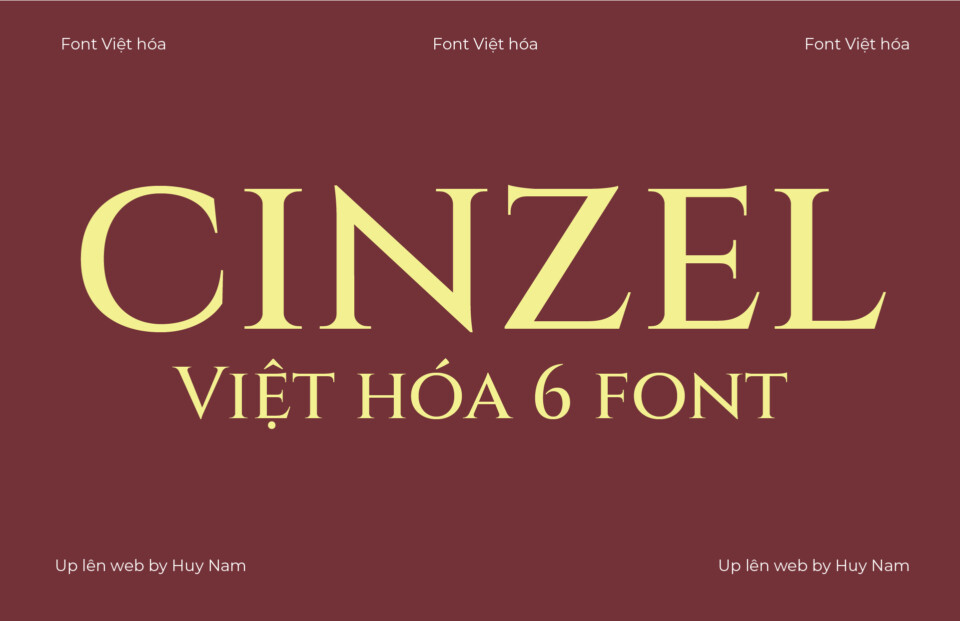
Font Việt hóa Cizel ( 6 font )
Tải Ngay Bộ Font Việt hóa Cizel ( 6 font ) Sang Trọng Cho Thiết Kế Cổ Điển
Trong thế giới đồ họa hiện đại, việc tìm kiếm một bộ Font Miễn Phí chất lượng cao luôn là ưu tiên hàng đầu của các nhà thiết kế. Đặc biệt, đối với những dự án mang phong cách cổ điển, uy nghi và mạnh mẽ, bộ Font Việt hóa Cizel ( 6 font ) chính là sự lựa chọn không thể bỏ qua. Cizel được lấy cảm hứng từ các ký tự khắc trên đá của đế chế La Mã cổ đại, mang đến một vẻ đẹp vượt thời gian nhưng vẫn đảm bảo tính ứng dụng linh hoạt trong các phần mềm thiết kế hiện nay. Với sự tỉ mỉ trong quá trình việt hóa, bộ font này giúp người dùng dễ dàng thể hiện các nội dung tiếng Việt mà không lo lỗi dấu hay khoảng cách chữ không đều, tạo nên sự đồng nhất hoàn hảo cho tác phẩm.
Đặc điểm nổi bật của bộ Font Việt hóa Cizel ( 6 font )
Thiết kế hình khối và tỉ lệ chuẩn mực
Bộ Font Việt hóa Cizel ( 6 font ) nổi bật với các nét chữ dứt khoát, thanh mảnh nhưng vô cùng vững chãi. Tỉ lệ giữa các ký tự được tính toán khoa học, mô phỏng lại phong cách Typography kinh điển của phương Tây thế kỷ trước. Điều này giúp bộ chữ không chỉ đẹp ở dạng tiêu đề lớn mà còn giữ được độ sắc nét khi trình bày ở các kích thước nhỏ hơn. Đặc biệt, các đường chân chữ (serif) được gọt giũa tinh tế, tạo cảm giác chuyên nghiệp và đẳng cấp cho người xem ngay từ cái nhìn đầu tiên.
Sự đa dạng với 6 biến thể khác nhau
Lý do bộ Font Việt hóa Cizel ( 6 font ) được ưa chuộng chính là sự đầy đủ trong các định dạng chữ. Bộ sưu tập này bao gồm 6 kiểu từ mảnh (Light) đến đậm (Black), cho phép bạn linh hoạt tùy chỉnh độ nhấn mạnh của thông tin. Bạn có thể dùng kiểu Regular cho các đoạn nội dung trang trọng và kiểu Bold hoặc Extra Bold để tạo ấn tượng mạnh cho các tiêu đề chính. Khả năng phối hợp giữa các biến thể trong cùng một bộ font giúp thiết kế của bạn có chiều sâu và tính phân cấp thông tin rõ ràng hơn bao giờ đối với người xem.
Ứng dụng thực tế của Font Việt hóa Cizel ( 6 font ) trong đời sống
Nhờ vào vẻ ngoài lịch lãm, bộ font này thường xuyên xuất hiện trong các thiết kế thương hiệu cao cấp như logo cho các thương hiệu thời trang, trang sức hoặc khách sạn. Ngoài ra, các bạn học sinh và giáo viên cũng có thể ứng dụng bộ chữ này vào việc làm bìa tiểu luận, thiệp mời sự kiện nhà trường hoặc các bài thuyết trình lịch sử để tăng thêm phần trang trọng. Khả năng hiển thị tiếng Việt trọn vẹn giúp thông điệp truyền tải một cách tự nhiên và đầy tính nghệ thuật, giúp người dùng tự tin hơn trong việc sáng tạo nội dung số.
Kết luận về giá trị của bộ font